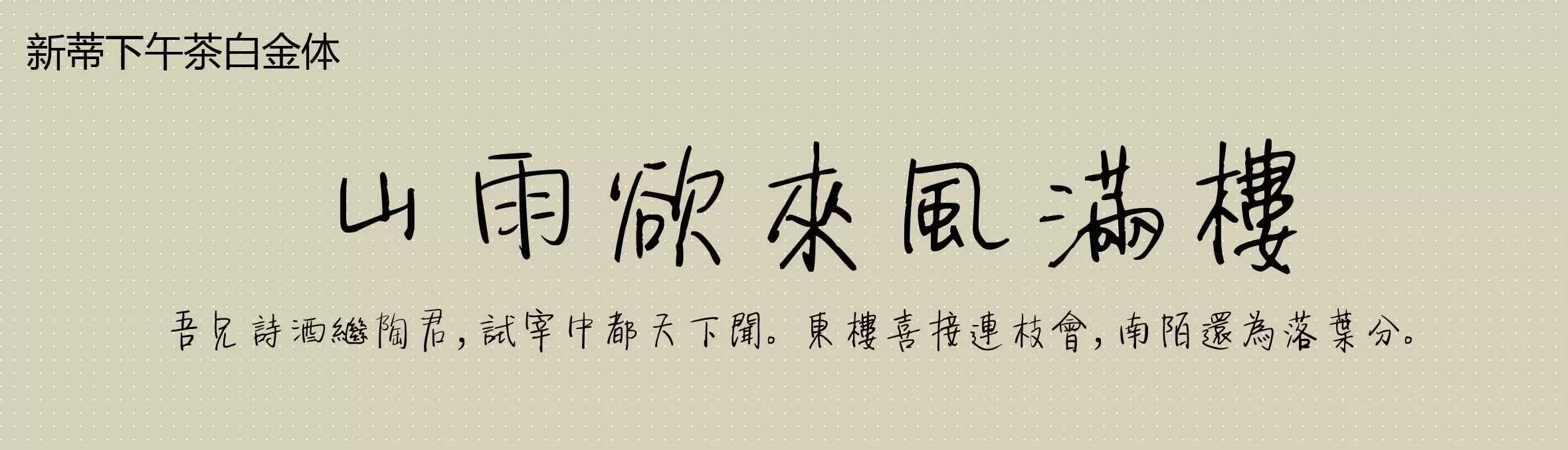
今天介绍的是“新蒂下午茶白金体”字体。
“新蒂下午茶白金体”是一款华丽精美的中文手写字体,它精美细致,灵动活泼,极具现代感。它的线条柔和流畅,字形清晰规整,非常适合用于印刷、包装设计、广告设计等领域。
这款字体的特色在于它的轻盈感和流畅感,使它非常适合用于设计带有时尚感的产品或服务。无论是设计网站、广告宣传、海报、书籍封面还是名片等,都可以使用“新蒂下午茶白金体”来增加视觉吸引力和品牌形象。
总之,“新蒂下午茶白金体”是一款优雅、别致、现代的中文手写字体,它将会为您的设计和创意带来新的灵感和惊喜。